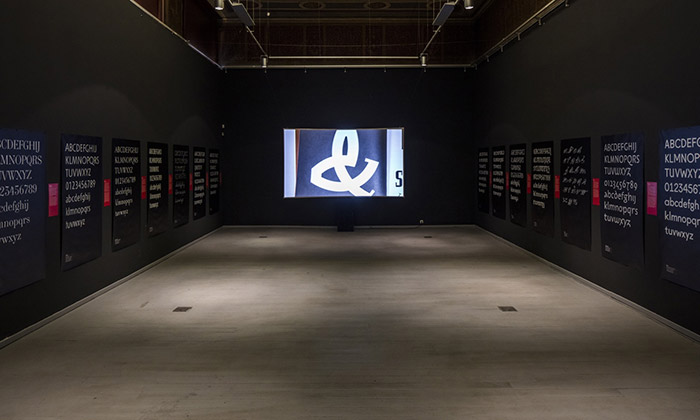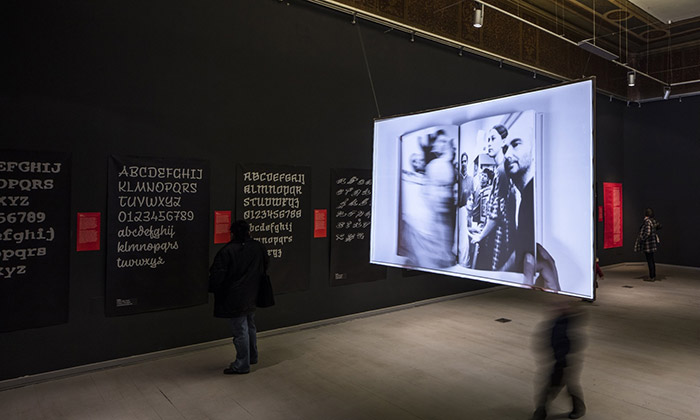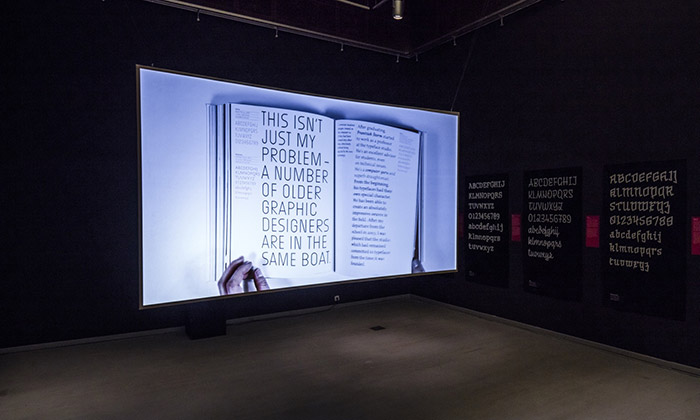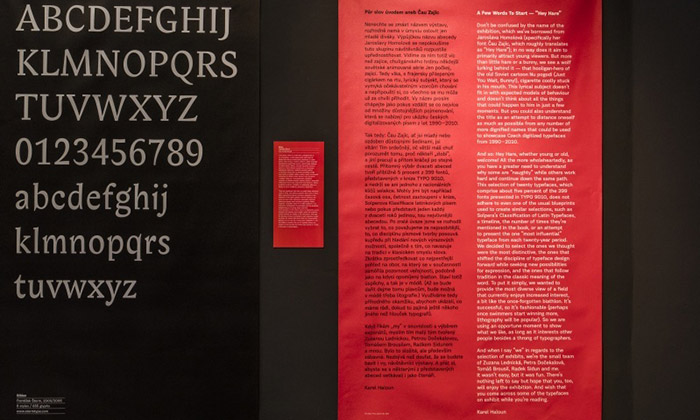
V pražské Galerii UM je až do 28. května otevřena výstava se zvláštním názvem Čau Zajíc a napovídajícím podtitulem TYPO 9010. Věnována je výhradně typografii a vybraných 20 nejzajímavějších abeced čerpá právě z knihy TYPO 9010, která nabízí české digitalizované písmo 1990–2010.
„Nenechte se zmást názvem výstavy, rozhodně nemá v úmyslu oslovit jen mladé diváky. Výpůjčkou názvu abecedy Jaroslavy Homolové se nepokoušíme tuto skupinu návštěvníků rozpustile upřednostňovat. Vidíme za ním totiž, víc než zajíce, chuligánského hrdinu někdejší sovětské animované série Jen počkej, zajíci. Tedy vlka, s frajersky přilepeným cigárkem na rtu, lyrický subjekt, který se vymyká očekávatelným vzorcům chování a nepřipouští si, co všechno se mu může už za chvíli přihodit. Vy název prosím chápejte jako pokus vzdálit se co nejvíce od množiny důstojnějších pojmenování, která se nabízejí pro ukázku českých digitalizovaných písem z let 1990–2010,“ říká spolukurátor výstavy Karel Haloun.
„Tak tedy: Čau Zajíc, ať jsi mladý nebo ozdoben důstojnými šedinami, jsi vítán! Tím srdečněji, oč větší máš chuť porozumět tomu, proč někteří „zlobí“ a jiní pracují a přitom kráčejí po stejné cestě. Přítomný výběr 20 abeced tvoří přibližně 5 procent z 399 fontů představených v knize TYPO 9010, se nedrží ani jednoho z racionálních klíčů selekce. Mohly jimi být například časová osa, četnost zastoupení v knize, Solperova Klasifikace latinkových písem nebo pokus představit jeden každý z dvaceti roků jedinou, tu nejvlivnější abecedu,“ dodává.